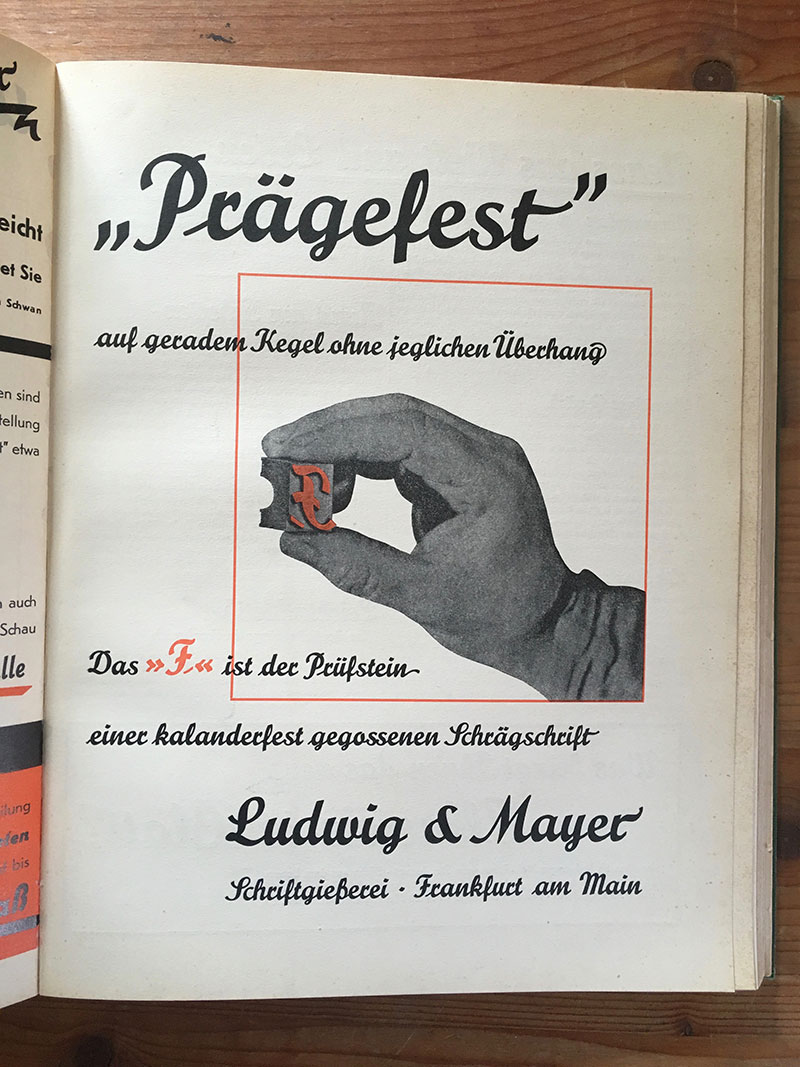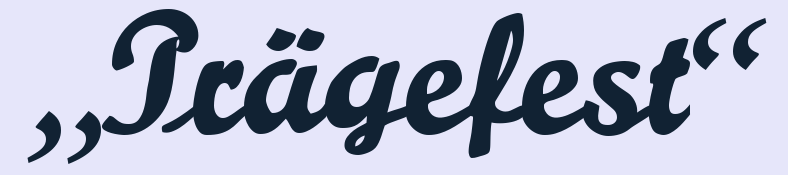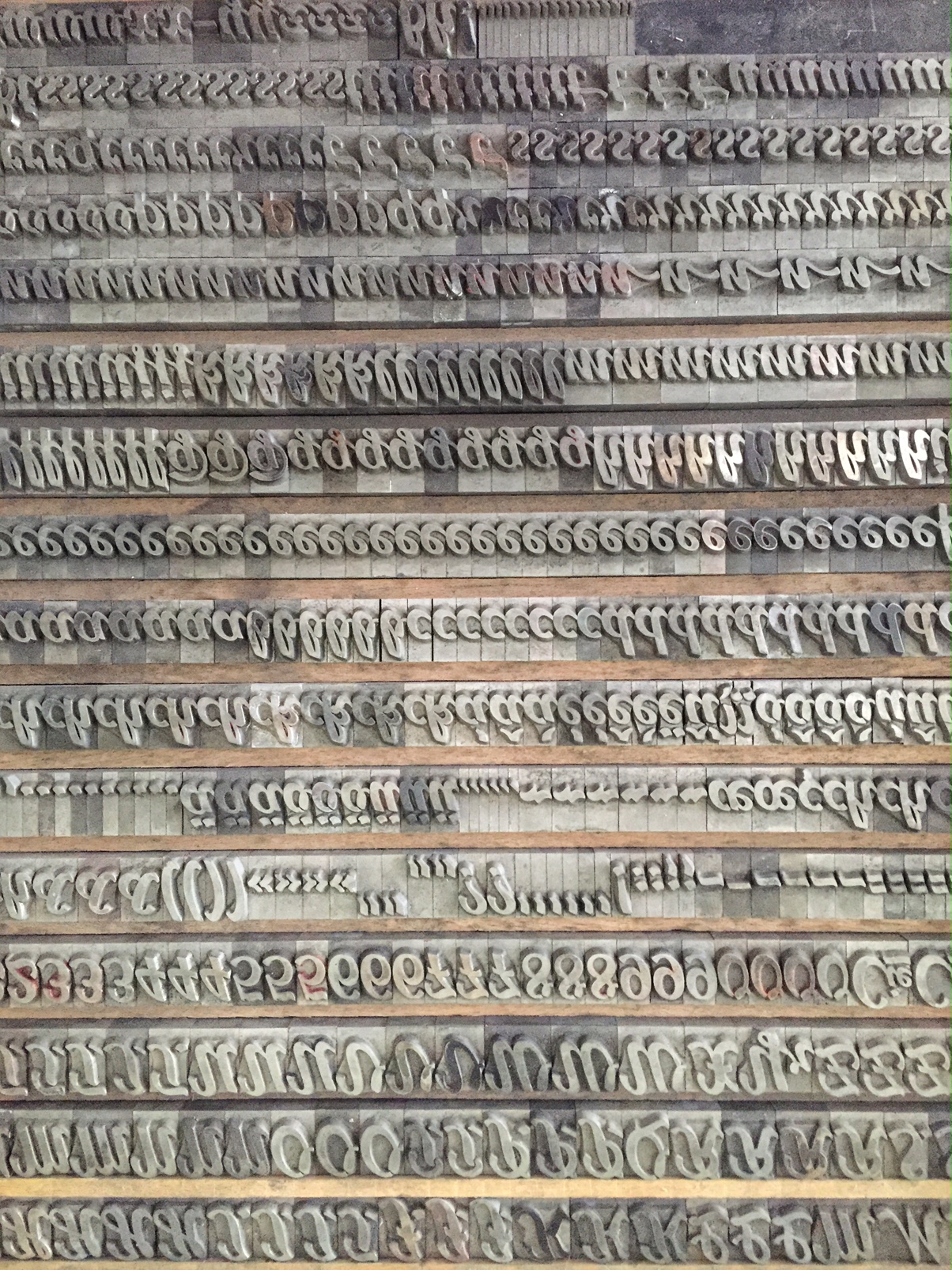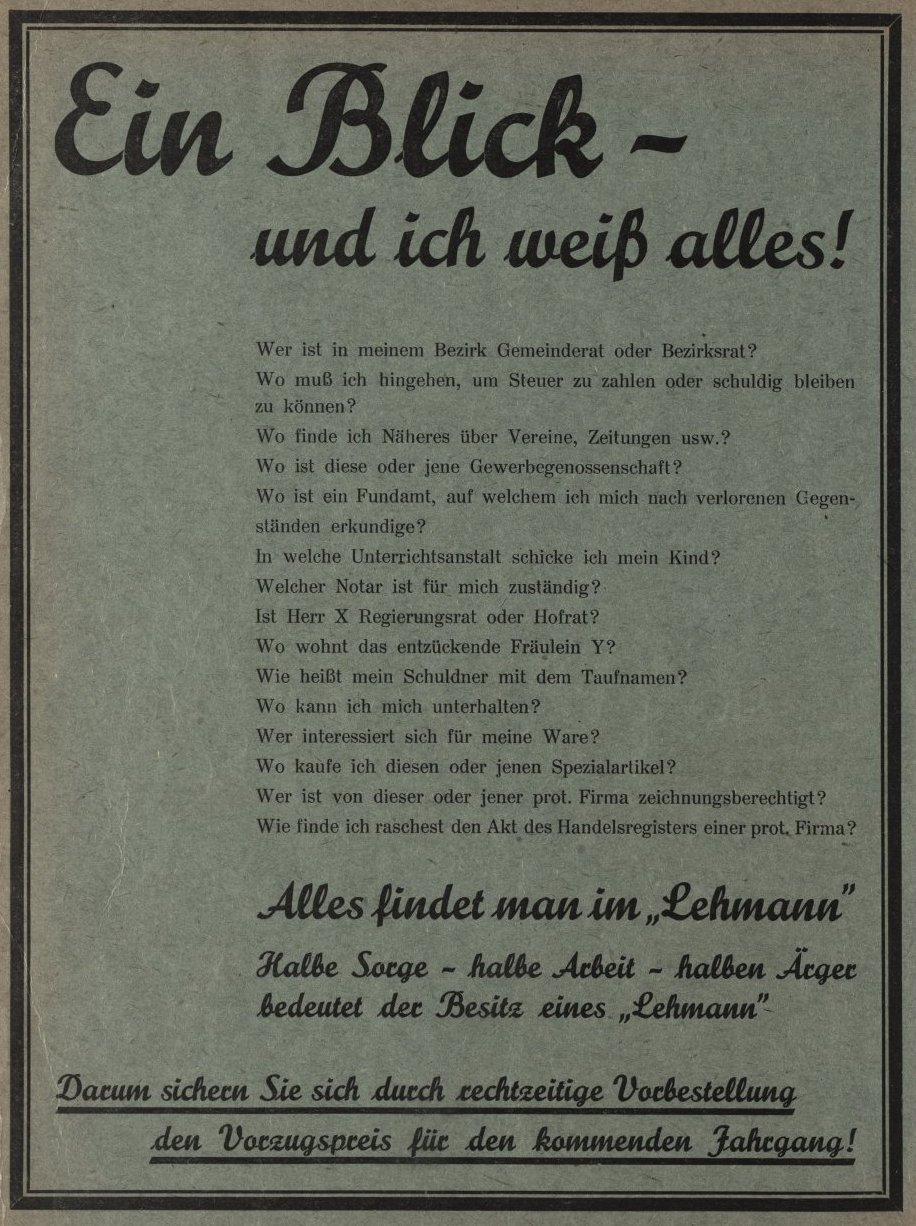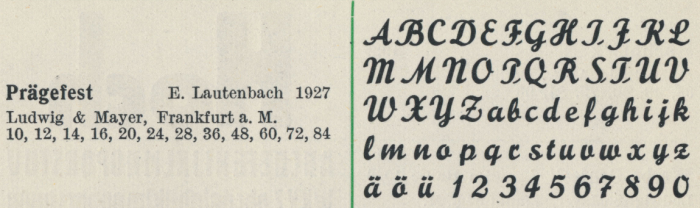
Prägefeste Bleisatz-Schriften
Hallo, »Bertholomäus«!
Ich war auch vier Jahre an tps und Serie M tätig, in Frankfurt. diatype, diatronic und diatext kenne ich noch von der Ausbildung in Kiel her, wo ich auch herstamme.
Seinerzeit definitiv der letzte Stand der Dinge in Sachen Digitale Typografie. Weltweit das erste System mit der sog. »Echtfontdarstellung«, d.h. statt grün leuchtender Umrisslinien sah man die echten Glyphen einer Schrift. Es hat dann aber noch einige Jahre gedauert, bis die gesamte Bibliothek der H.Berthold AG fertiggestellt war. Das waren ja auch 1.400 Schriften, alles Berthold-Exklusivschriften.
Ich habe mir einmal kurz die Mühe zu einer vergleichenden Darstellung gemacht. Das erste Bild zeigt einen Seitenbildschirm SBS 3001, das zweite ein GraphicTerminal (mit PixelGraphic eine ganz frühe Grautonbildverarbeitung, LineGraphic einer der Vorläufer von Illustrator, FreeHand, CorelDraw!), das damalige Flaggschiff.
Hier nun der SBS:
Und hier die »Echtfontdarstellung« – natürlich nur als Vorschau, darin arbeiten und mit der Maus anfassen und so ging dann erst mit PageMaker und dem Mac. An der Serie M musste man nach wie vor in der Berthold-Kommandosprache editieren. Das Satzprogramm für die Sun-Workstation hieß ProfiPage und war für reinen Text um den Faktor 10 schneller als PostScript.
Lars, Verzeih, das war jetzt "etwas" OT, auch wenn ich das als Willkommensgruß an ein Berthold-Affinen Neuankömmling durchaus verstehe, auch ich freue mich hier über jeden weiteren Fachmann aus allen Regionen typografischer Beschäftigung.
Doch zurück zu den Prägefesten:
Könnte es sein, dass die speziell als Prägefest angebotenen Bleischriften, also nicht die weiter oben ewähnten Alu-Zink Lettern, oder die sicher auch prägefesten, irgendwo anders vorgestellten Messinglettern, sondern eben die aus dem normalen Letternmetall möglicherweise einen weniger steilen Konus hatten?
Ich könnte mir vorstellen, dass dies beim Prägedruck den Vorteil einer besseren Abstützung der Lettern-Kanten bringt, beim normalen Druck aber leichte Nachteile dadurch bringen könnte, dass praktisch die Flanken ein winziges Maß mit drucken.
Nein, Peter, dass die Prägeschriften einen steileren Konus aufwiesen, ist mir nicht bekannt. Es waren halt Spezialschriften mit in der Tat etwas einfacherer Zeichnung, also ohne filigrane Überhänger oder dergleichen. Eine Englische Schreibschrift wäre da nicht drin gewesen.
Übrigens hatte ich meinen Beitrag versehentlich zu früh abgeschickt, ich hatte noch ein »Aber zurück zum Ursprungsthema« begonnen, dann aber irgendwie versenkt. Ich hatte noch schreiben wollen, dass bei den Kieler Nachrichten, meinem späteren Lehrbetrieb, die gesamten Seiten in einen blauen Spezialkarton gepresst, selbiger in eine eine Form gebogen und zu einem halben Zylinder geformt, dann ausgegossen wurde. Damit wurde dann gedruckt, und weil ein so ein Stereo nicht die ganze Auflage durchhielt, musste die Maschine ich glaube zweimal zum Zylindertausch gestoppt werden. Zum Herstellen dieser Mater wurden jedoch ganz normaler Linotypesatz und Satzschriften sowie Klischees für den Kopf und die Bilder gemischt gepresst. Aber diese Art der Formherstellung fällt wohl gar nicht unter »Prägefest«.
Ich kenne diese Bezeichnung eigentlich nur als eine Sammlung von speziellen, eigens zum Zweck der Prägung angefertigten Schriften, die eine andere Legierung hatten und eben einfacher waren, damit sie dem Druck und der Hitze auch standhielten.
Übrigens hat sie Paul wetzig seinerzeit wohl gar nicht für beachtenswert gehalten, jedenfalls taucht keine einzige im »Seemann« auf.
Wie Lars.schwarz Richtigstellte, bedeutet „prägefest” eine Information für die Bubis (Buchbinder), und auch für den Büttendruck. Prägefeste Schriften gab es auch für Blindprägungen.
Mhh, also für mein Verständnis hilft dies der Aufklärung nicht unbedingt.
Lars sprach von zwei ganz unterschiedlichen Dingen und vermied für »Prägetypen« den Begriff »prägefest«, der hier nun wieder explizit genannt und ausdrücklich auf Buchbinder bezogen wird, obwohl der Titel dieses Stranges »prägefeste Bleisatz-Schriften« ist. Also wie nun? Kam der Begriff »prägefest« wirklich für beide Dinge zum Einsatz, die eigentlich nichts miteinander zu tun haben? Das wäre doch seltsam. Und wie wurden die prägefesten Bleisatz-Schriften nun eigentlich benutzt? Was wurde da wie und warum geprägt?
…, die gesamten Seiten in einen blauen Spezialkarton gepresst, selbiger in eine eine Form gebogen und zu einem halben Zylinder geformt, dann ausgegossen wurde. Damit wurde dann gedruckt, und weil ein so ein Stereo nicht die ganze Auflage durchhielt, musste die Maschine ich glaube zweimal zum Zylindertausch gestoppt werden. Zum Herstellen dieser Mater wurden jedoch ganz normaler Linotypesatz und Satzschriften sowie Klischees für den Kopf und die Bilder gemischt gepresst. Aber diese Art der Formherstellung fällt wohl gar nicht unter »Prägefest«.
Ich dachte es ginge genau darum bei »prägefest« …
Beim Prägen von Einbänden etc. hat man doch andere Werkzeuge, oder täusche ich mich?!
Ja, da hat man andere Werkzeuge. Ich habe mal exemplarisch eine kleine Handpresse (mit so etwas bin ich übrigens in Kontakt mit Bleilettern und Winkelhaken gekommen*) und einem richtig fetten Teil, das praktisch eine Tiegelpresse mit beheiztem Fundament ist (auf etwa 120°). Das Angebildete Teil prägt auf einer Fläche etwa A1 !!!
(gibts da Vorlagen?)
Halbe Sorge – halbe Arbeit – halben Ärger
Wie es aussieht, gibt es hier andere Gedankenstriche:
Hier ein Bild meiner kürzlich erstandenen Bleisatz-Prägefest in 3 Cicero. Wie man sehen kann, sind auch ein paar Schwungbuchstaben dabei (g, n, r, t).
Das Versal-M hat auch 2 verschiedene Formen (unten rechts im Bild zu sehen). Ich habe die Lettern erst kürzlich bekommen und noch nicht in einen Stecksatzkasten einsortieren können, daher das stellenweise Durcheinander.